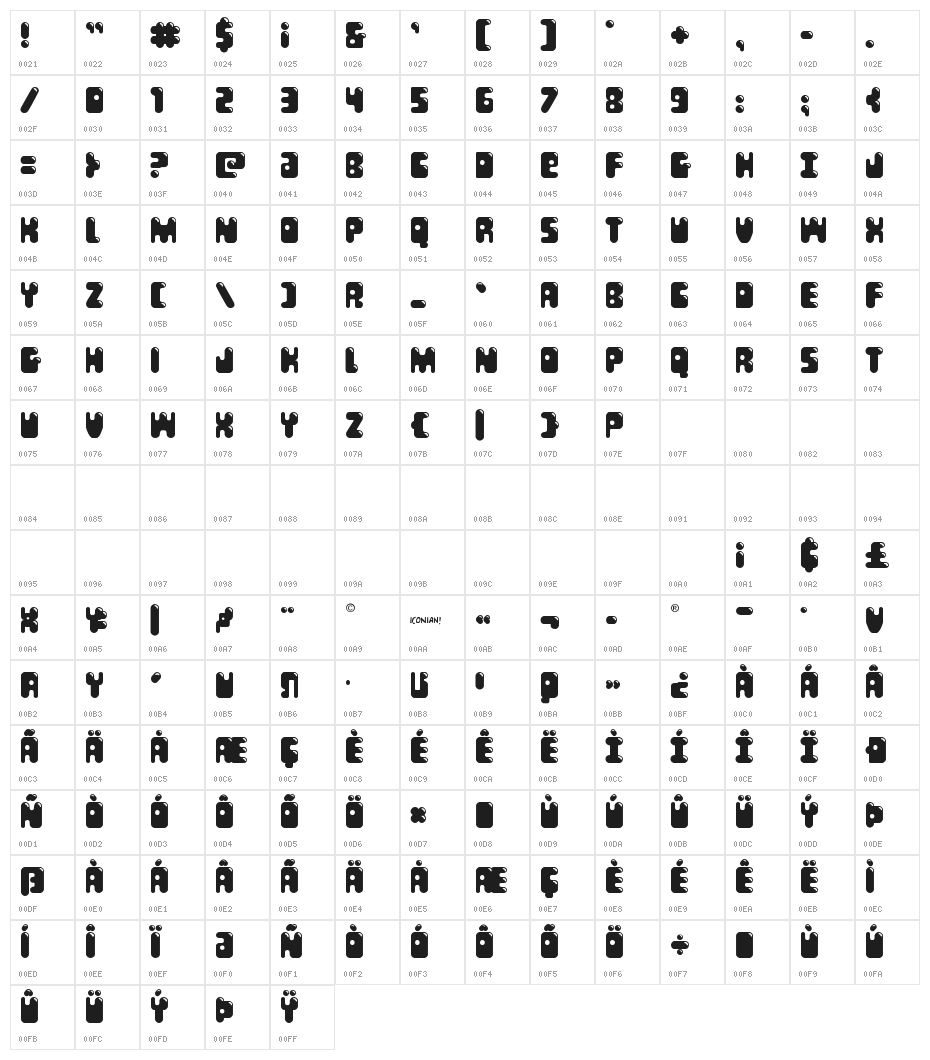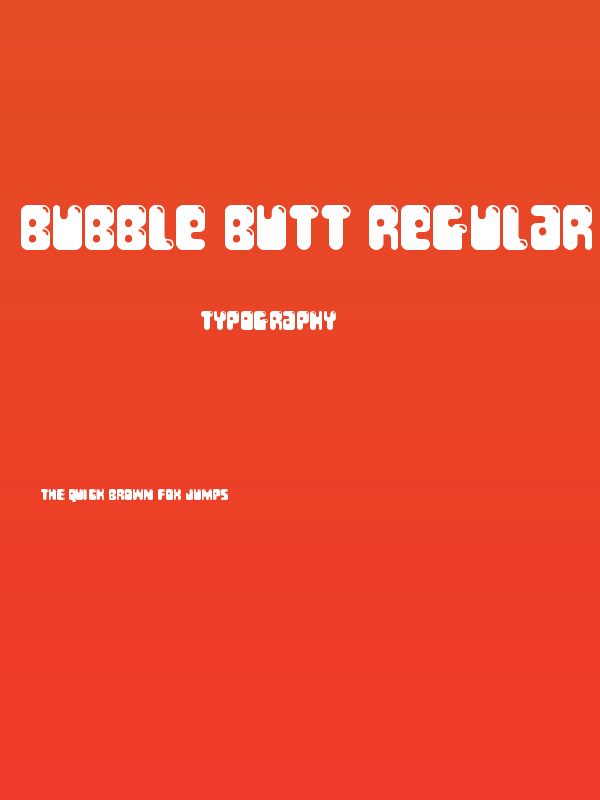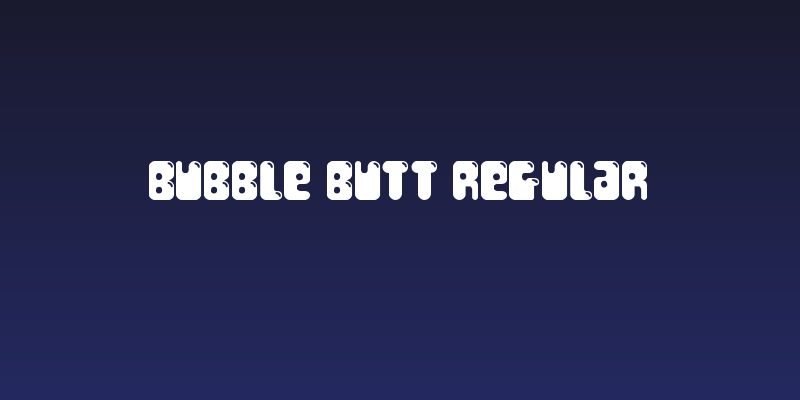
Bubble Butt Regular Font
| Gesamtstil | Playful, Quirky |
| Vorgeschlagene Projekte | Ideal for children's books, playful branding, party invitations, and creative posters. |